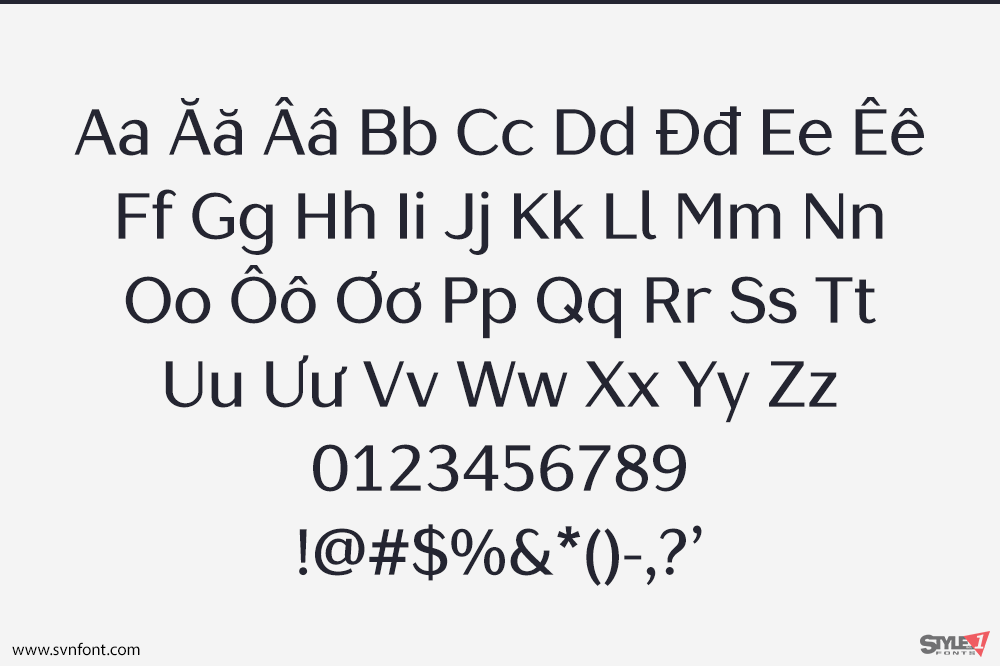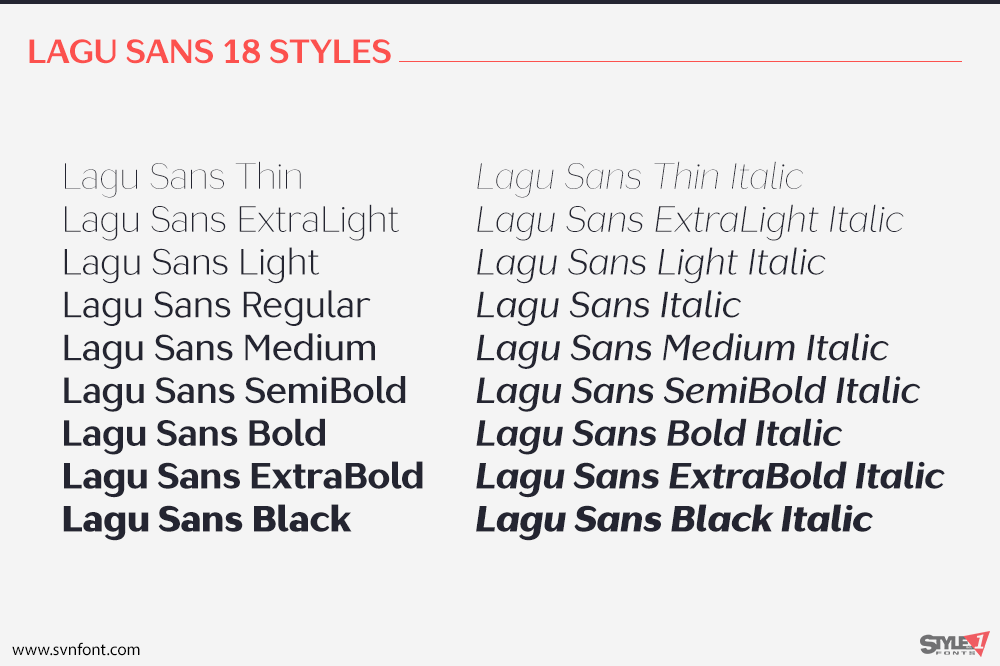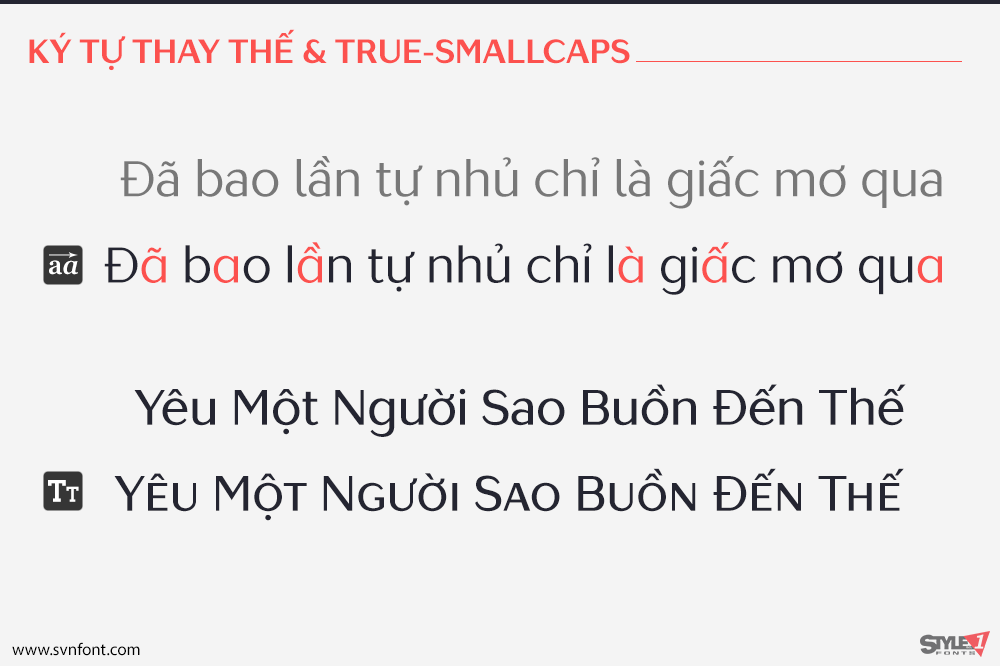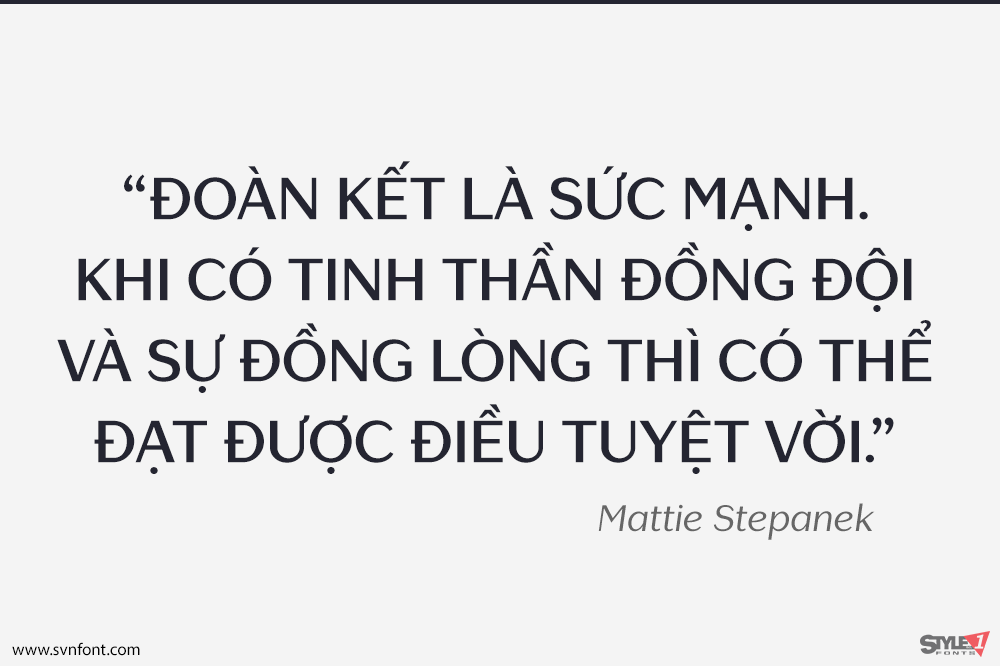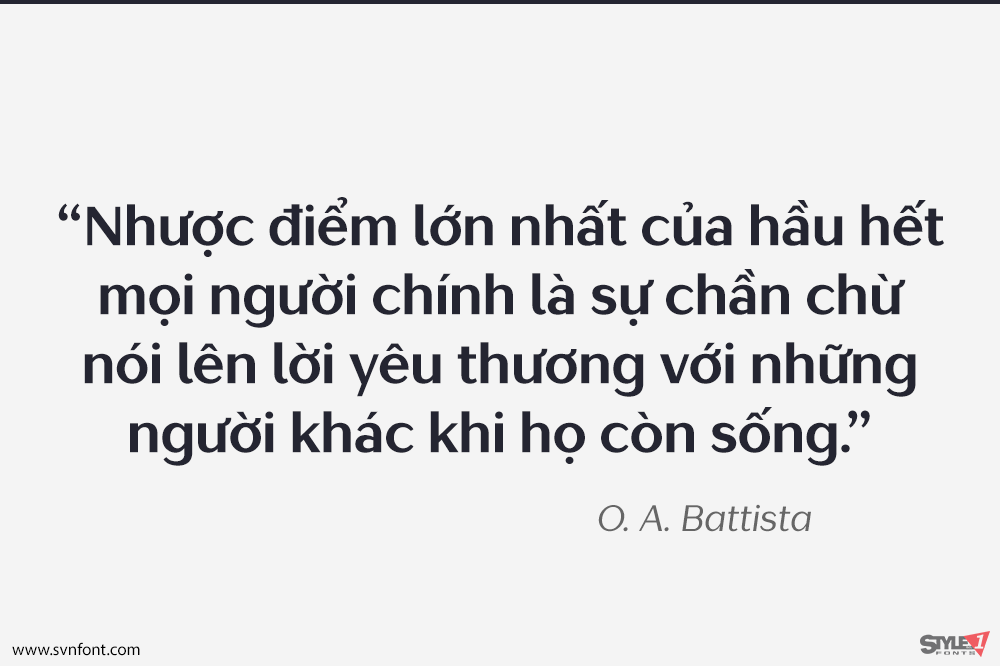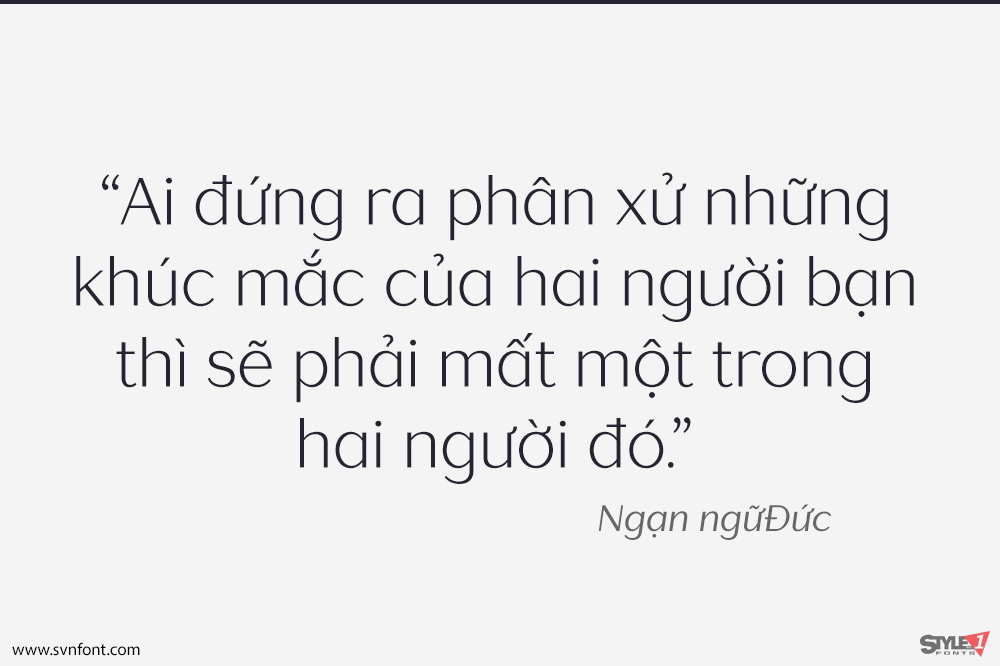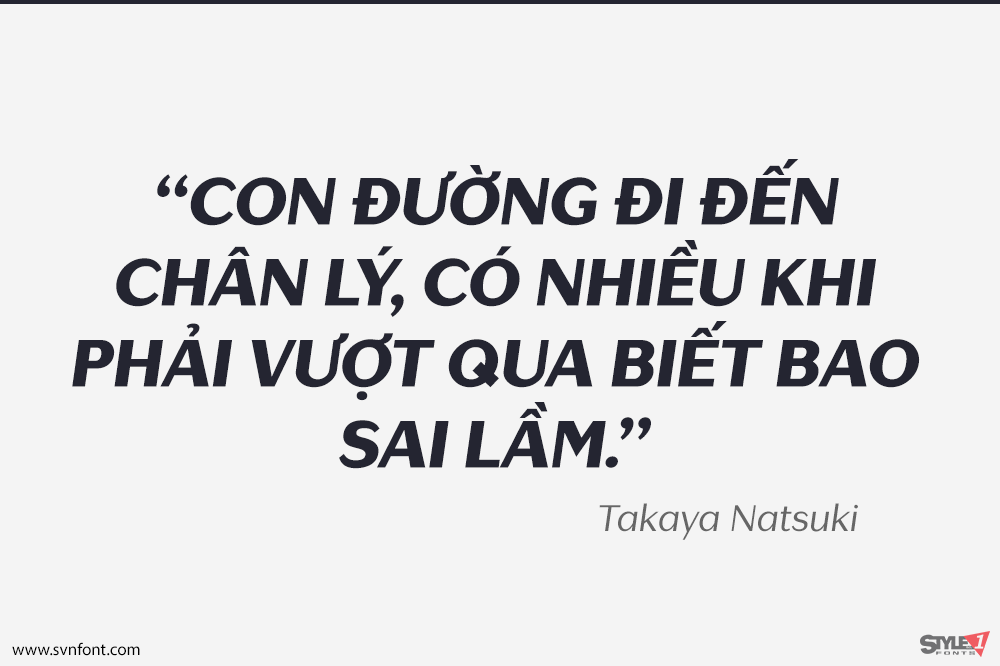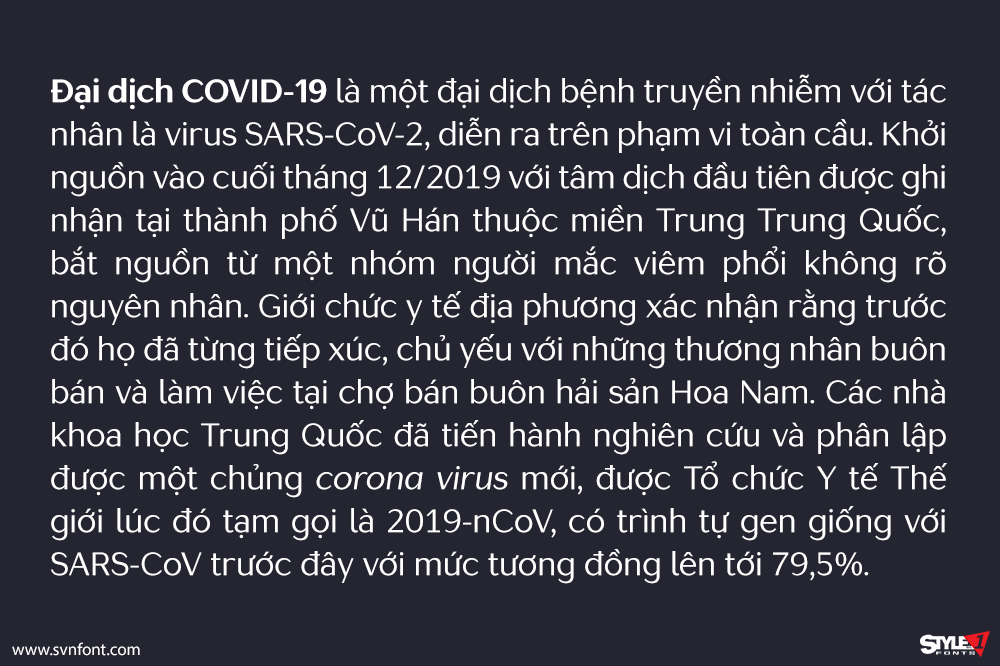
Lagu Sans là một kiểu chữ đương đại kết hợp giữa cảm hứng hình học và độ tương phản duyên dáng giữa các nét dày và mỏng. Alessio Laiso đã thiết kế Lagu Sans với 18 kiểu: 9 độ đậm từ Thin đến Black, cùng với các kiểu chữ nghiêng đẹp mắt tương ứng.
Phông chữ đồng hành Lagu Serif biến bộ phông Lagu trở thành một “workhorse” (phông chữ đa năng, mạnh mẽ) thực sự cho mọi mục đích sử dụng, bao gồm web, kỹ thuật số, in ấn, xây dựng thương hiệu và biển báo.
Lagu Sans có chiều cao x-height lớn và các nét mở, giúp nó dễ đọc. Phông chữ này đi kèm với các tính năng OpenType mạnh mẽ, bao gồm chữ ghép (ligatures), ký tự thay thế (alternative glyphs), chữ in hoa nhỏ (small caps), phân số, số dạng bảng (tabular figures), số kiểu cũ (old-style figures), và nhiều hơn nữa. Bộ phông chữ Lagu hỗ trợ 219 ngôn ngữ, bao phủ 100% bộ ký tự Latin Plus.
Nhà thiết kế: Alessio Laiso
Nhà phát hành: Alessio Laiso Type